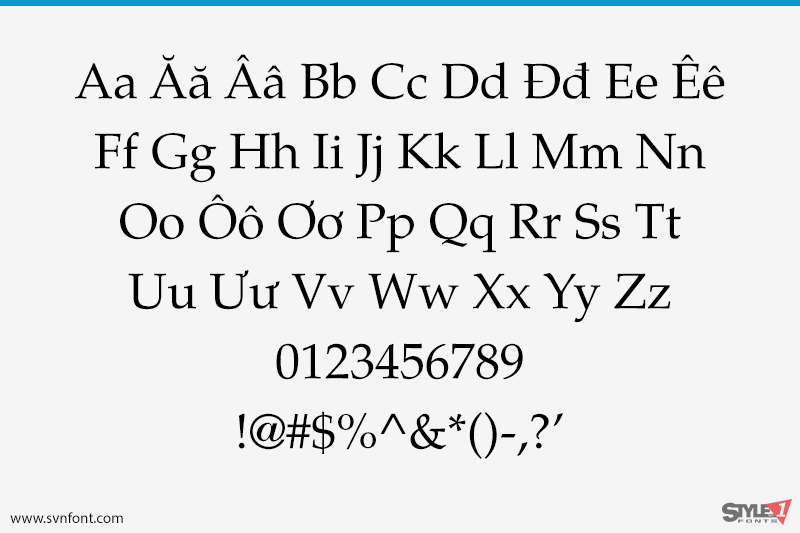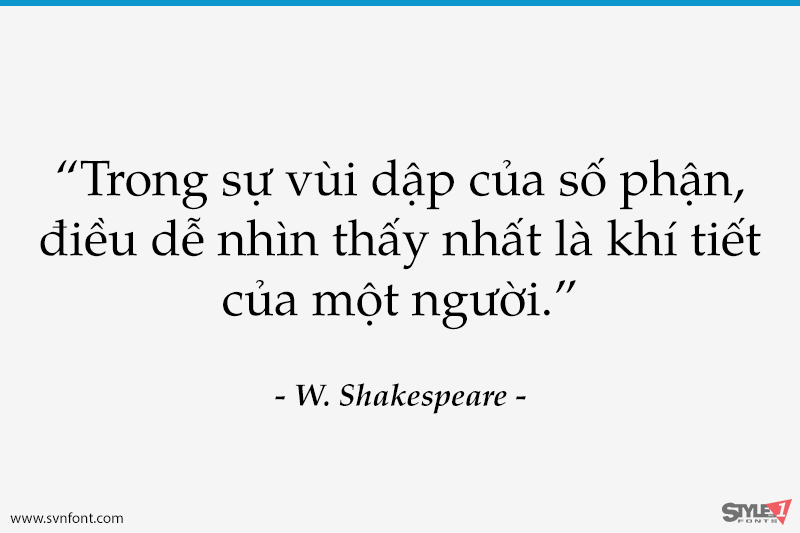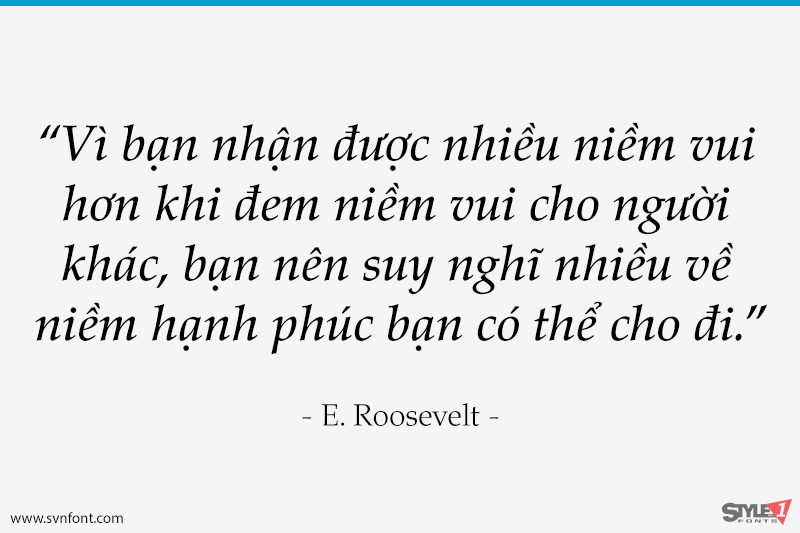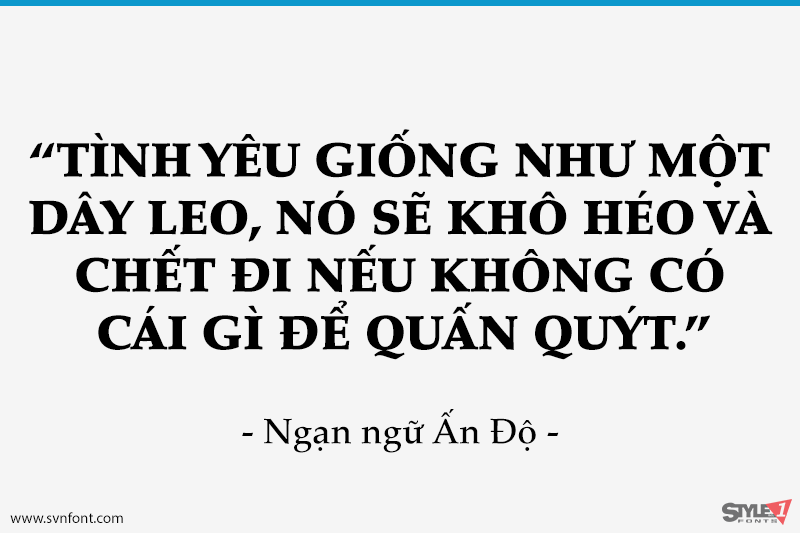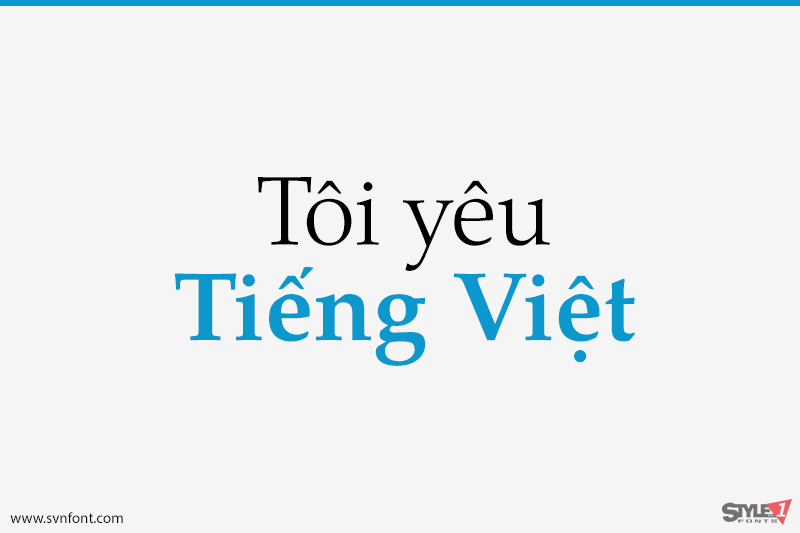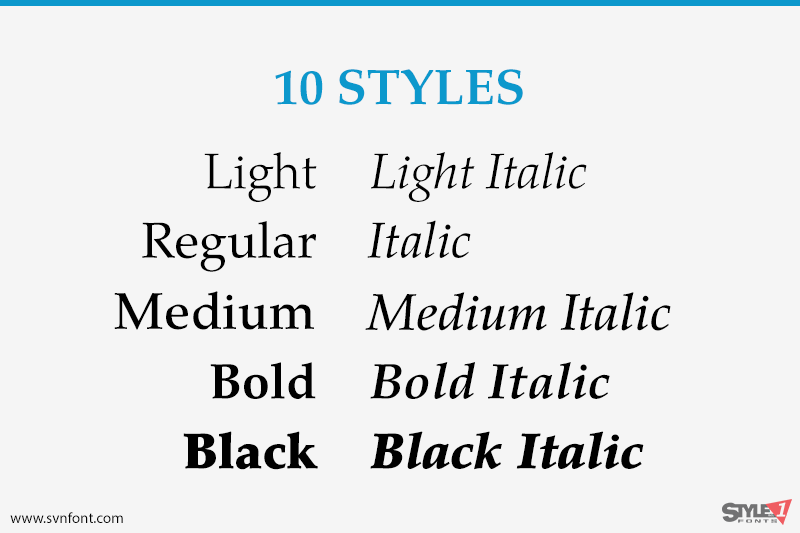
Palatino là tác phẩm của Hermann Zapf và được phát hành vào cuối những năm 1950 bởi D. Stempel AG tại Frankfurt am Main. Zapf đã tối ưu thiết kế của Palatino nhằm tăng khả năng đọc, tạo ra một kiểu chữ vẫn rõ ràng ngay cả khi in trên loại giấy kém chất lượng trong giai đoạn hậu Thế chiến II.
Zapf đặt tên font theo Giambattista Palatino, một bậc thầy về thư pháp sống cùng thời với Leonardo da Vinci. Palatino là một font thuộc nhóm Old Face, minh chứng rằng những hình thức cổ điển vẫn có thể được sử dụng để tạo nên các kiểu chữ mới.
Nhà thiết kế: Hermann Zapf
Nhà phát hành: Monotype